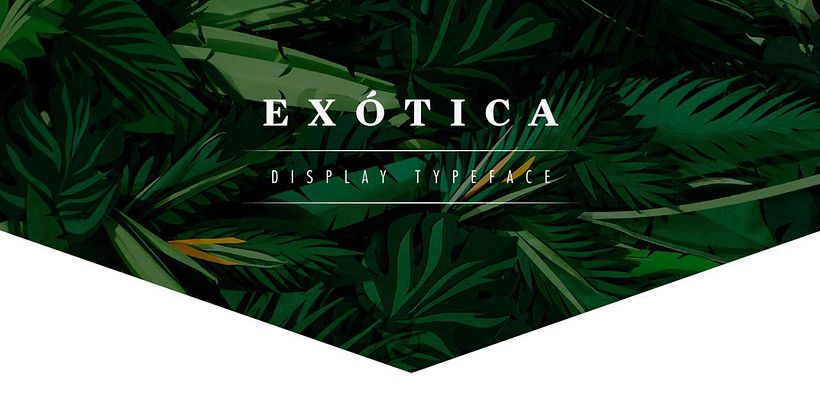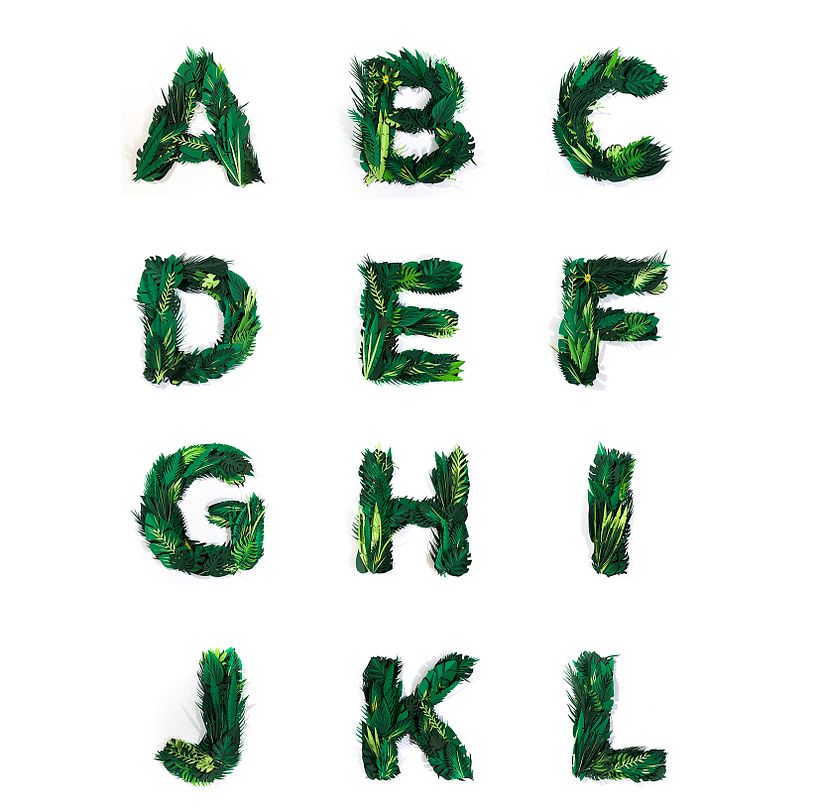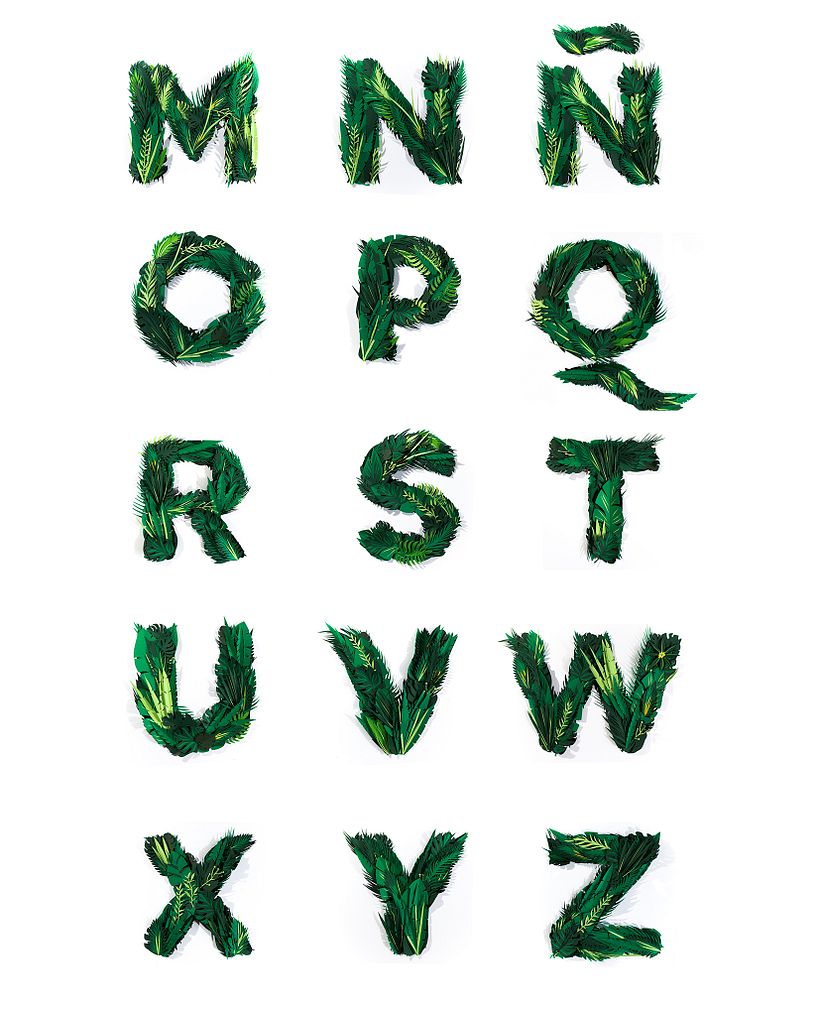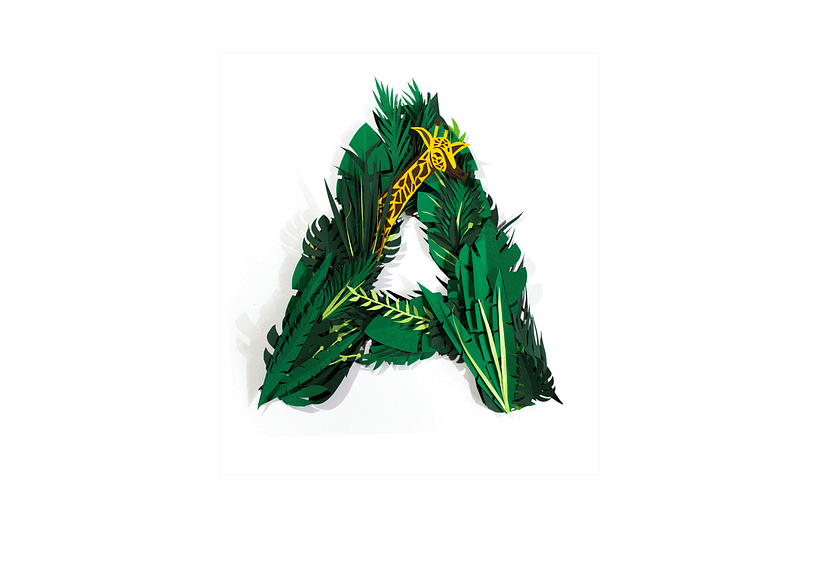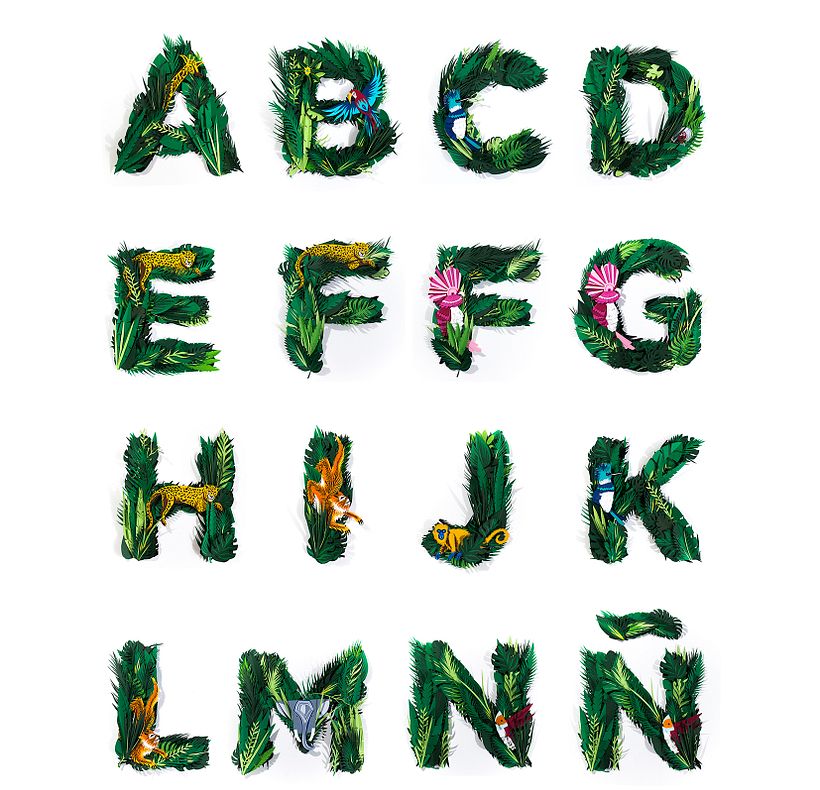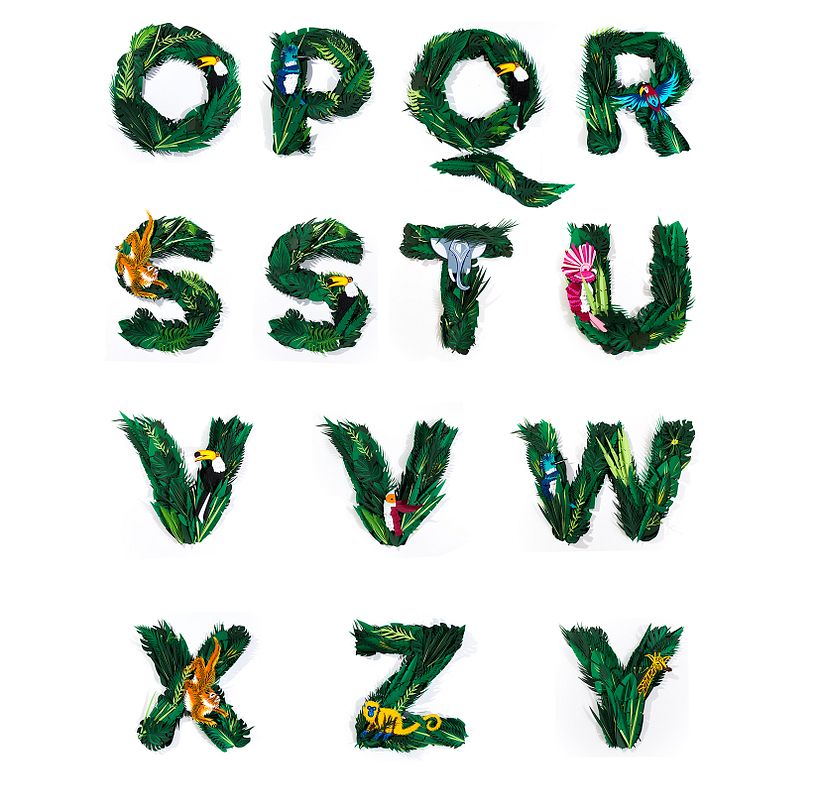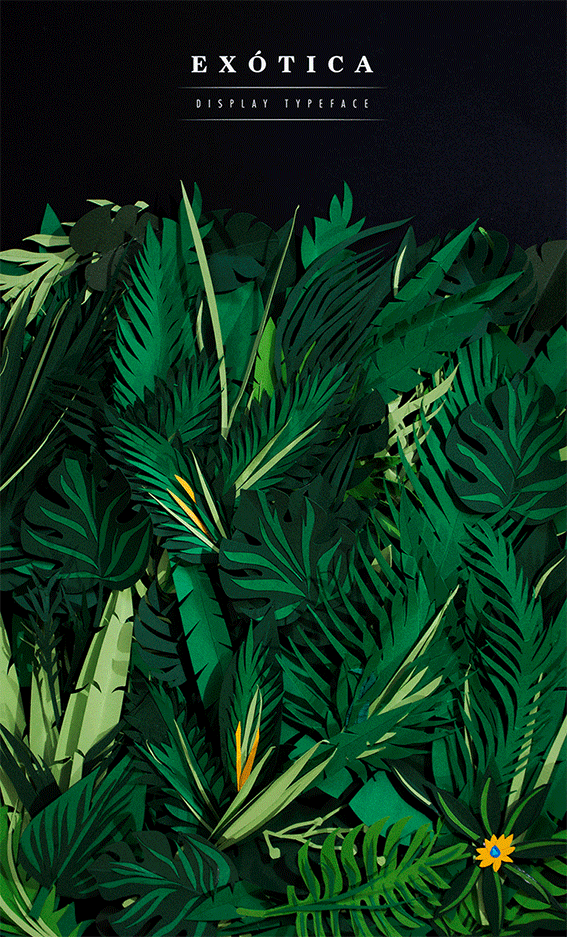
Exótica - Display typeface
ESP Exótica es una tipografía display llegada directamente desde la selva amazónica,
el bosque tropical más extenso del mundo, que se desarrolla alrededor del río Amazonas y de su cuenca fluvial.
Allí las altas temperaturas favorecen el desarrollo de una vegetación siempre verde.
Exótica es el resultado de combinar experimentación con un proceso de trabajo manual y artesanal.
Elaborada en papel, esta tipografía display representa la más tupida y exuberante vegetación tropical.
Compuesta por un set de glifos donde se han planteado letras alternativas para mejorar la composición estética en textos.
La idea nace en la Escuela Superior de Diseño de Aragón, donde se nos propuso la realización de un ejercicio de temática libre.
Un trabajo que nos ha permitido demostrarnos que las cosas se pueden hacer bien si se invierte esfuerzo y pasión,
y que trabajar en equipo siempre suma.
ENG Exotica is a display typeface which came directly from the largest tropical forest in the world,
which is developed around the Amazon River . There, the high temperatures favor the development of an ever green vegetation.
This display typeface contains 74 letters – 2 alphabet sets with an animal version and another one without animal
and a glyphs set with alternates to improve aesthetics composition on display texts.
Exotic is the result of the combination of experimentation with manual and craftwork processes.
Elaborated in paper, this typography represents the most dense and exuberant tropical vegetation.
The idea was born in the Superior School of Design of Aragon, where we were proposed for the realization of an free project .
Its a project that has allowed us to prove that things can be done well if you invest in it effort and passion.
And that teamwork always adds and enhances projects.